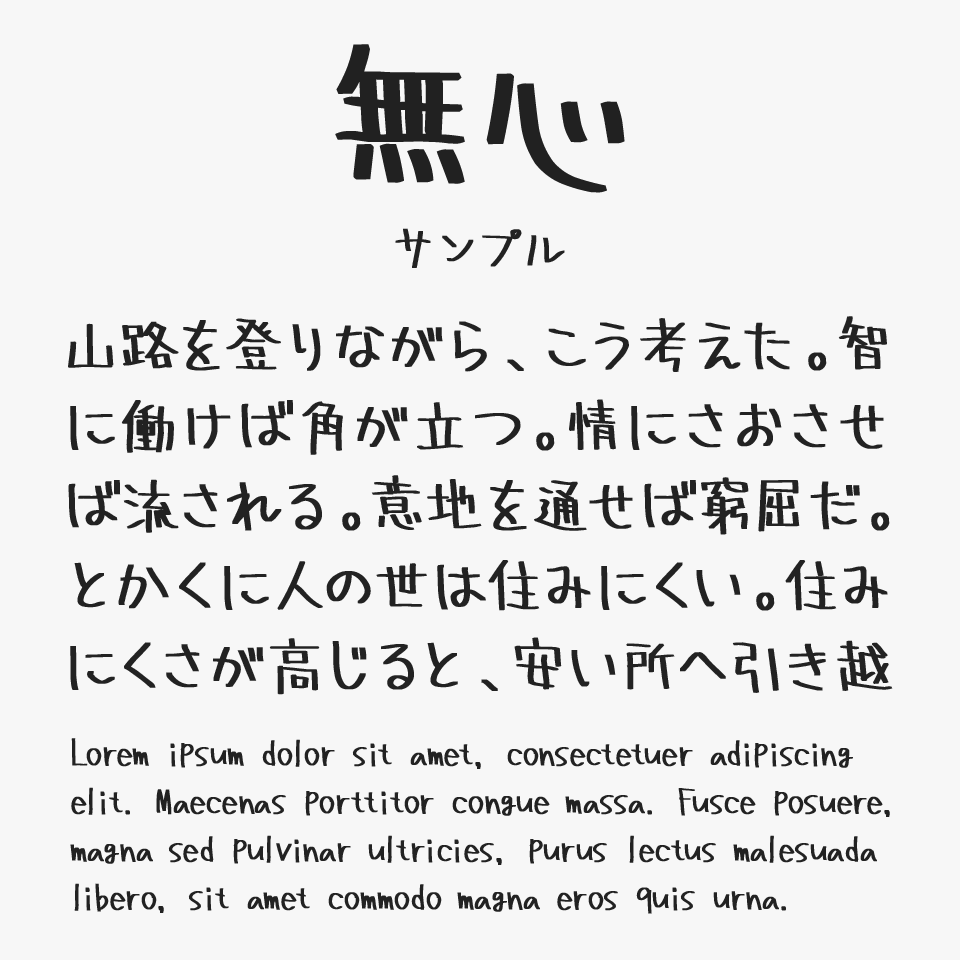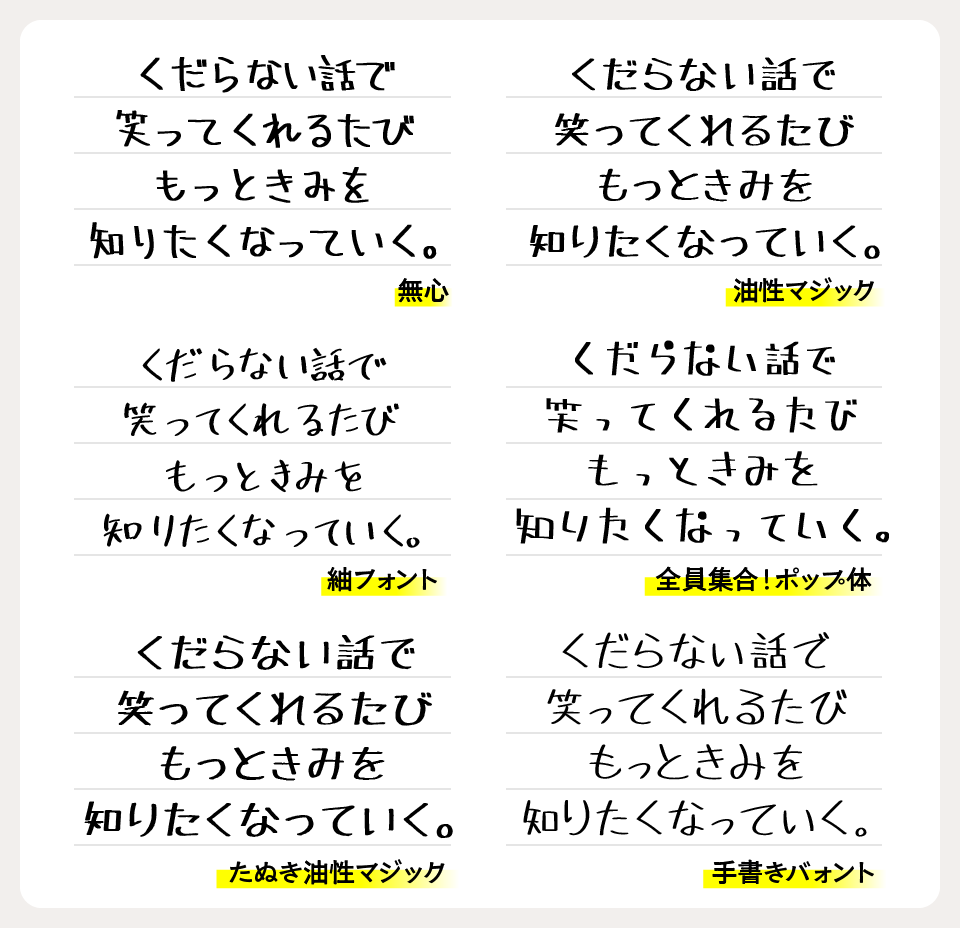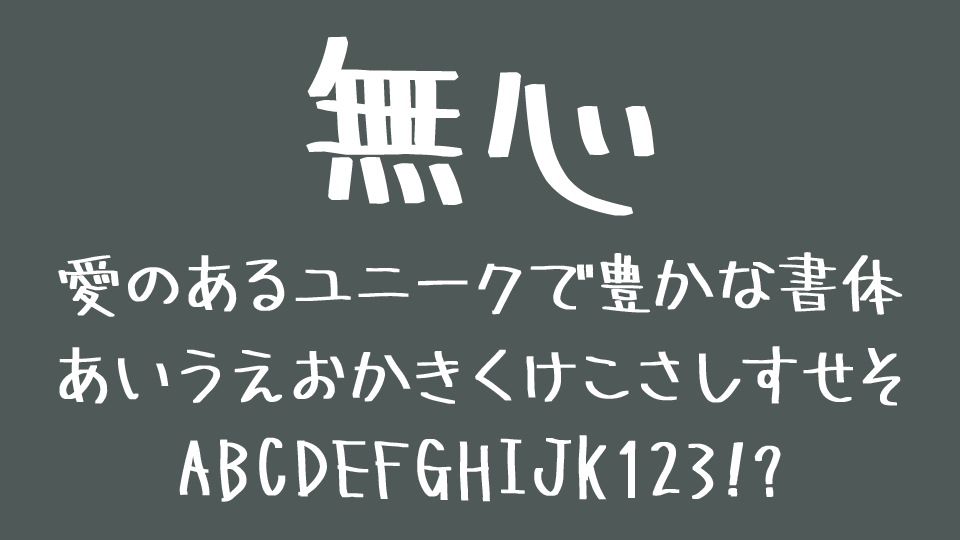
無心(むしん)フォントは、その名前の通り、“ただひたすら無心で殴り書きした文字”をそのままフォント化したような、ラフで味わい深い手書きフォントです。
特別なテーマや整ったデザインコンセプトを意識するのではなく、作者の方が勢いのまま書いた文字を活かしているため、自然な雑さや力の抜けた空気感がなんとも言えない味わいがあり、太めのマーカーで書いたような太さの手書きフォントです。
“整っていなさ”が逆に良いアクセントになっており、ゆるさや無気力感を表現したいデザインとも相性抜群です。
MV風デザインやサブカル系ビジュアル、メモ書き風タイトルなどにもぴったりで、“脱力感が妙にクセになる”魅力を持った人気の手書きフォントです。
無心フォントを、ほかの太めのマーカーやサインペンで書いたような雰囲気を持つ手書きフォントと比較してみると、ラフさをそのまま活かした“脱力感”が特に魅力的なフォントです。
比較フォントは、「油性マジック」「紬フォント」「全員集合!ポップ体」「たぬき油性マジック」「手書きバォント」と使用していますが、どのフォントも独特な書き味がステキな手書きフォントなので、ぜひあわせてチェックしてみてください。
収録文字は、ひらがな・カタカナ・第一第二水準漢字・IBM拡張漢字となっています。